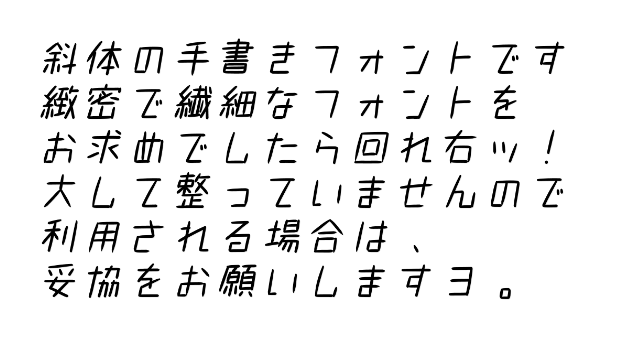
菜鳥救星分享:免費字體下載-851テガキカクット 發佈日期: 2021-01-212021-02-08 作者: Natty 文、菜鳥編 今天要分享的字體是851テガキカクット,你可能會覺得眼熟,跟小編之前分享的一款字體名稱相似,其實是與851チカラヅヨク為同一個開發者。這款字體的特色就是在於具有斜體的手寫筆畫,使用軟體中的斜體效果,如果覺得傾斜角度過大,不妨就試試這款字體,應該會給你有滿意的感覺! 字體名稱:851テガキカクット下載位置:http://bit.ly/2ULZQgy 進到網頁可以看到字體內容的表現,字體在2016年11月就停止更新,但小編使用上漢字的支援是還不錯的。 大家關心的是否可商業使用,在網站上也有聲明。 網頁的最上方就可以看到下載點了。 下載下來的檔案只有一個字體安裝檔,開啟安裝即可。 字體在Adobe與Office中名稱不同。 Adobe中: Office中: 免費字體為網路搜尋而來,使用權限請以官方文件與說明為主 加入菜鳥救星官方Line並回覆「我想看文章」,不定期獲得更多知識吧! 不同頻道,不同知識! Facebook Instagram Youtube 分享此文: 分享到 X(在新視窗中開啟) X 分享到 Facebook(在新視窗中開啟) Facebook 分享到 Telegram(在新視窗中開啟) Telegram 以電子郵件將連結傳送給朋友(在新視窗中開啟) 電子郵件 請按讚:喜歡 正在載入... 相關